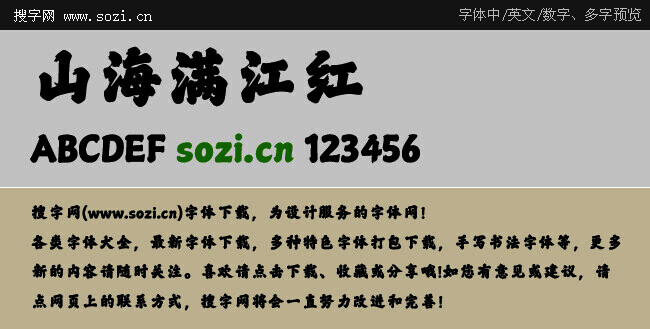
山海滿江紅
搜字網(wǎng)提供一款山海滿江紅中文書法字體下載,該字體雄健有力,霸氣外露,在粗細(xì)的縱橫間,擁有非常規(guī)的張力特性。該字體的筆畫充滿力量感,組合搭配極富強(qiáng)烈的節(jié)奏感,融入楷書特點(diǎn),飛白縱橫其間,使字體的視覺效果有力、寬厚、方正,充滿了穩(wěn)重感和設(shè)計(jì)感。適合包裝設(shè)計(jì)、海報(bào)設(shè)計(jì)、廣告設(shè)計(jì)等應(yīng)用。